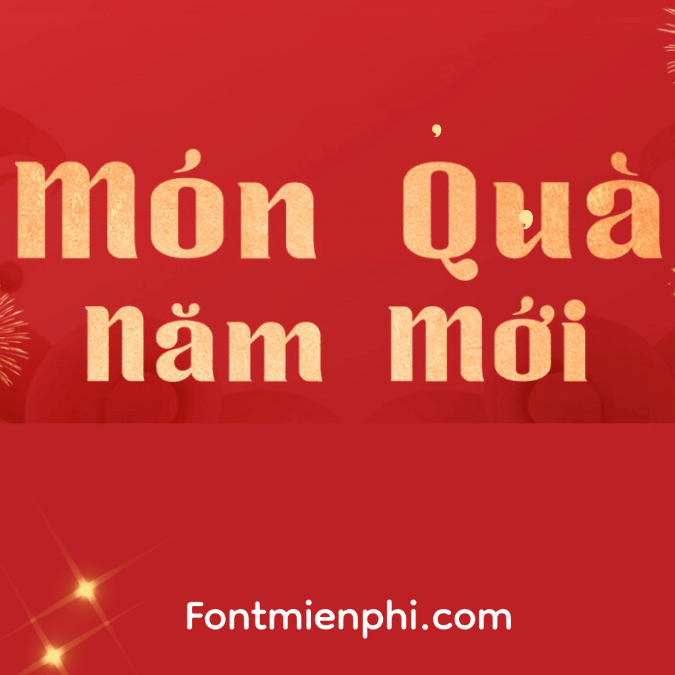
Font Việt hóa 1FTV VIP Zoika Font tết
Font Việt hóa 1FTV VIP Zoika
Font Việt hóa 1FTV VIP Zoika là một trong những kiểu chữ được ưa chuộng trong cộng đồng thiết kế đồ họa và in ấn tại Việt Nam. Với đặc điểm nổi bật, font này mang đến sự kết hợp hoàn hảo giữa tính thẩm mỹ và khả năng sử dụng linh hoạt trong nhiều lĩnh vực khác nhau.
Được thiết kế với các ký tự tiếng Việt được hỗ trợ đầy đủ, 1FTV VIP Zoika không chỉ đảm bảo tính chính xác trong việc hiển thị ngôn ngữ mà còn tạo cảm giác dễ đọc và thân thiện với người dùng. Chữ cái có độ dày vừa phải, giúp tăng cường khả năng nhận diện và tạo ấn tượng mạnh mẽ cho người xem.
Ngoài ra, font này còn có thiết kế hiện đại với các đường nét mềm mại, mang lại cảm giác gần gũi và dễ chịu. Điều này khiến nó trở thành lựa chọn lý tưởng cho các ứng dụng như logo, bìa sách, quảng cáo và nhiều sản phẩm truyền thông khác. Sự linh hoạt trong kiểu dáng cũng cho phép nó dễ dàng phối hợp với nhiều phong cách thiết kế khác nhau, từ hiện đại đến cổ điển.
Tóm lại, font Việt hóa 1FTV VIP Zoika không chỉ là một công cụ hỗ trợ thiết kế mà còn là một phần quan trọng trong việc xây dựng thương hiệu và truyền tải thông điệp một cách hiệu quả.